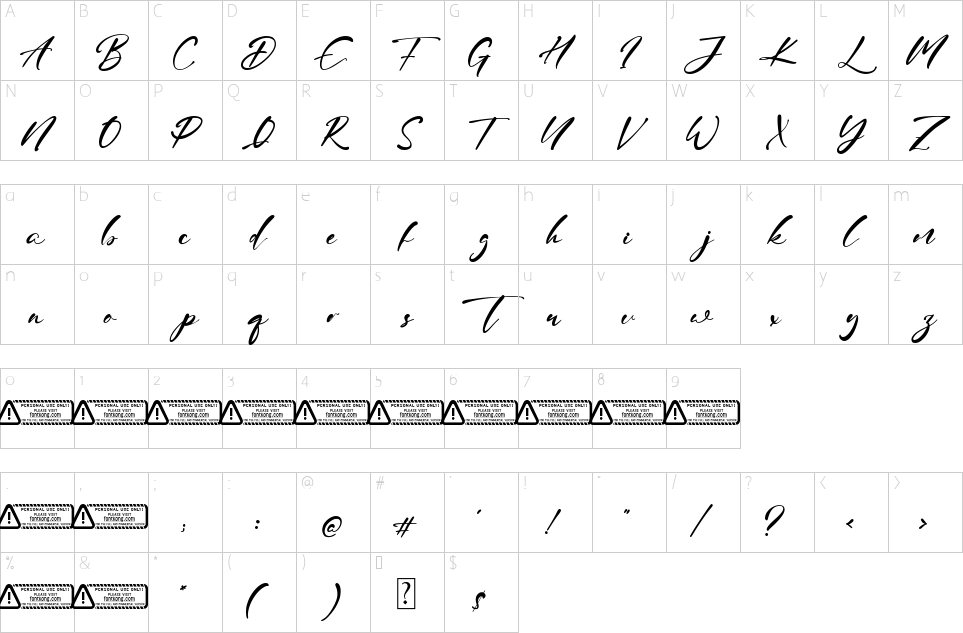
Descubra a fonte Julian Daniel, uma opção gratuita e versátil para seus projetos digitais. Desenvolvida pelo designer Font Kong, Julian Daniel oferece um estilo elegante e fácil de ler, ideal para aplicativos de texto, banners e até materiais de marketing. Com seu design cuidadosamente projetado, essa fonte é perfeita para quem procura uma opção gráfica e moderna sem precisar recorrer a versões pagas. Julian Daniel tem sido baixado mais de 3.416 vezes, o que comprova sua popularidade e qualidade. Para usufruir dessa fonte gratuita e versátil em seu ambiente Windows ou Mac, é simplesmente uma questão de um clique. Instale-a e personalize seu design de maneira elegante e profissional.